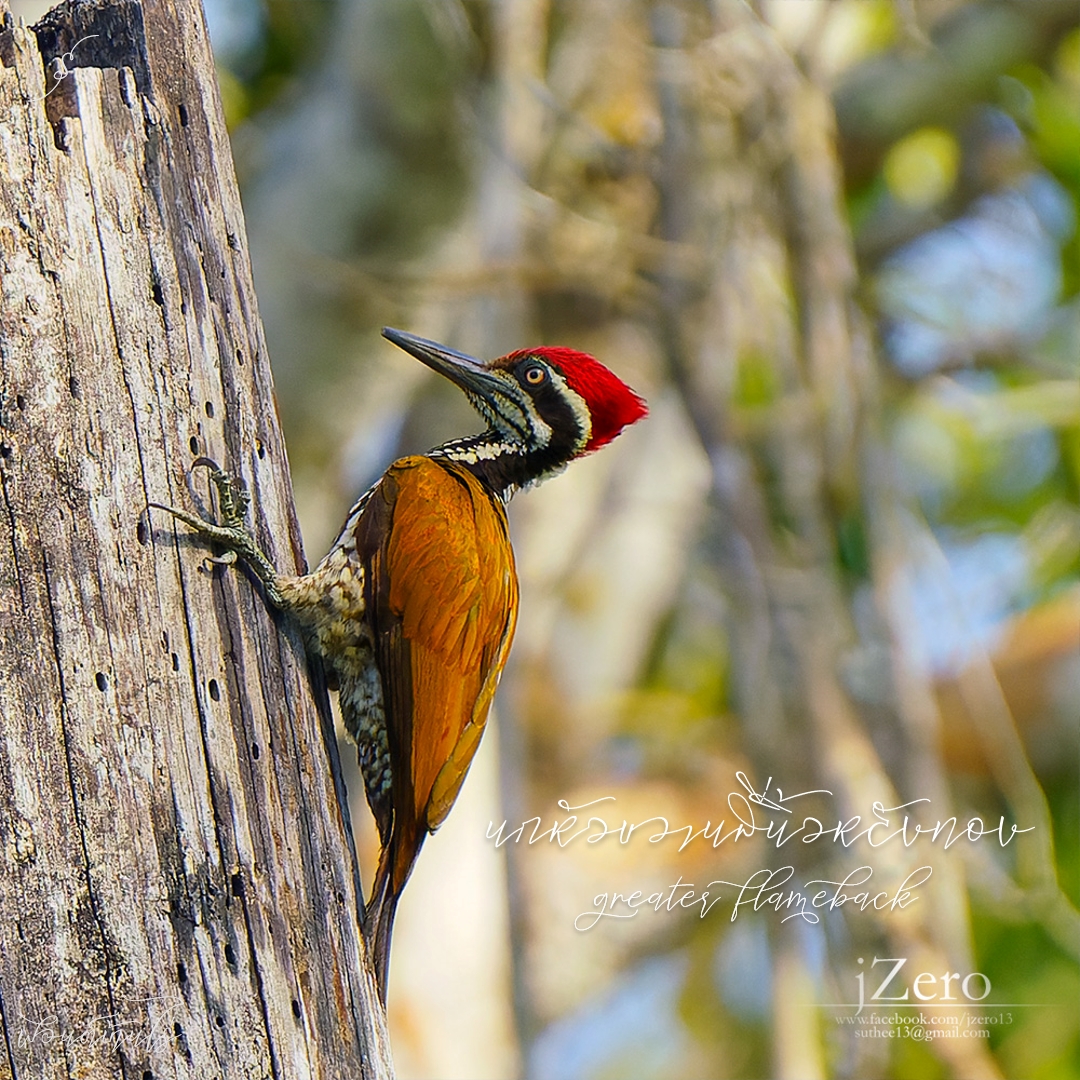
ฟอนต์ บ้านไร่
ฟอนต์บ้านไร่ ลายเส้นปากกา แนว advanced modern calligraphy ภาษาไทย .. อ่านไม่ง่ายเหมาะใช้ประกอบฟอนต์หลัก หรือวัตถุหลักอื่นๆ
ชื่อฟอนต์ : บ้านไร่
ฟอนต์บ้านไร่ ลายเส้นปากกา แนว advanced modern calligraphy ภาษาไทย .. อ่านไม่ง่ายเหมาะใช้ประกอบฟอนต์หลัก หรือวัตถุหลักอื่นๆ